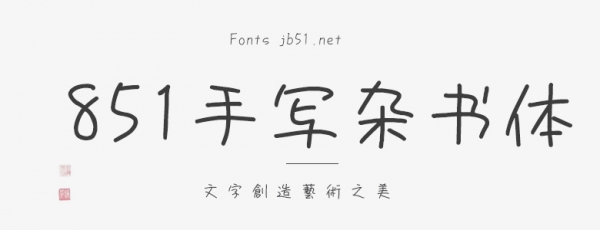
851手寫雜書體字體是一款賞心悅目的手寫字體,線條活潑優(yōu)美,筆畫優(yōu)雅,結(jié)構(gòu)肆意灑脫,具有很好的視覺感,字體文件格式為TTF,同時(shí)提供免費(fèi)在線預(yù)覽,免費(fèi)在線轉(zhuǎn)換以及免費(fèi)下載。
這款字體在電腦中顯示名稱為299-上首王朝體